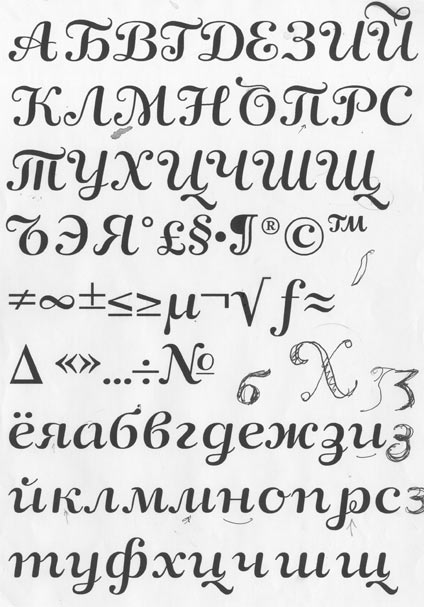
Одежда для беременных: Русские Шрифты Карандаш
Дизайнерский объёмный шрифт без поддержки русского языка. Добавлено: 19 Декабря 2012 | Просмотров: 20222.
Русский Карандаш Шрифт. На данный момент широко распространена возможность скачать шрифты. Причём, эта опция всё набирает популярность.
19 . Russian (есть русский алфавит — из серии тонкие шрифты кириллица).
Лучшие Платные Русские Шрифты (A). Этой статьей мы открываем серию, посвященную лучшим
Готические шрифты с поддержкой кириллицы. Русский (кириллический) шрифт из игры Quake.
Шрифты, стилизованные под клинопись, с поддержкой русских букв.
Русские рукописные шрифты удачно имитируют надписи, сделанные от руки с помощью руч��и, карандаша, пера или любой иной пишущей принадлежности.
Шрифт для фотошопа — Карандаш. [ ] 09.10.2009, 12:55. Интересный шрифт для photoshop.
Hagin — Газетный русский шрифт с засечками.
«Русские Декоративные Шрифты» Russ Decorative fonts. Искреннее восхищение вызывает то упорство, усидчивость, трудолюбие и целеустремленность людей…
Шрифт для надписей на чертеже (Чертежный шрифт) — Тема Линии чертежа — Уроки черчения — Каталог статей
Все надписи на чертежах должны быть выполнены чертежным шрифтом (рис. 24).
Начертание букв и цифр шрифта устанавливается стандартом. Стандарт определяет высоту и ширину букв и цифр, толщину их линий обводки, расстояние между буквами, словами и строками. Чтобы научиться надписывать чертежи стандартным шрифтом, надо знать не только характер начертания букв и цифр, но также и их размеры.
Стандарт устанавливает следующую высоту (она обозначается h, читается «аш») прописных (заглавных) букв и цифр: 2,5; 3,5; 5; 7; 10 и 14 мм.
Высота прописных букв (рис. 25) в миллиметрах соответствует размеру шрифта.
Ширина большинства прописных букв равна 4/7 высоты.
Исключение составляют буквы Ж, Ф, Ш, Щ, Ы, Ю, ширина которых равна 6/7 h, и букв А и М, ширина которых равна 5/7 h, т. е. немного меньше высоты. Нижние и боковые отростки букв Д, Ц, Щ, Ъ, цифры 4 и верхний элемент буквы Й выполняются зa счет промежутков между строками и буквами
Эти соотношения установлены для основного чертежного шрифта.
Однако стандарт разрешает использовать и широкий шрифт. Ширина букв такого шрифта больше тех же букв основного шрифта на 1/7 h.
Буквы и цифры чертежного шрифта имеют наклон к линии строки примерно 75° (рис. 25). Некоторые надписи допускается выполнять без наклона.
Высота строчных букв равна 5/7 высоты прописных букв
(рис. 25), что примерно соответствует высоте следующего меньшего размера шрифта. Например, высота строчных букв для шрифта 10 будет равна 7 мм. Исключение составляют буквы б, в, д, р, у и ф.
Ширина строчных букв равна 3/7 h, кроме букв ж, т, ф, ш, щ, ы, ю, ширина которых равна примерно их высоте, и буквы м, имеющей ширину 4/7 h.
Цифры имеют те же размеры, что и прописные буквы,кроме цифры 1; ее ширина 2/7 h.Расстояние между буквами и цифрами в словах принимают равным 2/7 h, между словами и числами не менее ширины букв текста. Расстояние между нижними линейками строк должны быть равны не менее 1.5 h.
Высота букв и цифр на чертежах, выполненных в карандаше, должна быть на менее 3,5 мм. Толщину линий букв и цифр выбирают равной примерно 1/7 h
Рукописные шрифты пишутся ручкой, карандашом или маркером.
Шрифты, поддерживающие кириллицу fontspring:
Семейство рукописных шрифтов sf, предназначенных для образовательных и печатных целей с использованием ручки или карандаша .